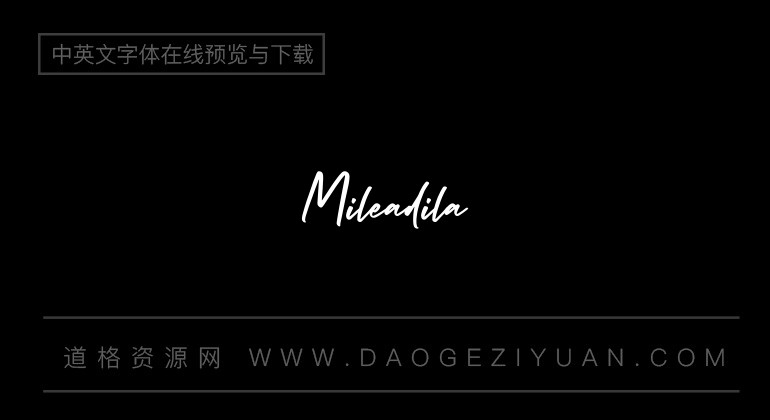
Mileadila 是一款简约的英文字体,它的字形简洁大方,字体层次分明,笔画流畅,给人一种灵动的感觉。Mileadila 字体的字形特征是圆润的笔画,比较轻盈,比较灵动,比较有节奏感,字体的笔画细腻,精致,极具艺术感。它适用于各类设计,特别是用于报刊杂志、海报、广告、网页等设计中。内容介绍
Mileadila是一款非常不错的手写艺术字体,具有很好的视觉感,适合于文化类的宣传设计、商业类品牌的广告和产品包装设计以及个性化文字排版等较多场景。